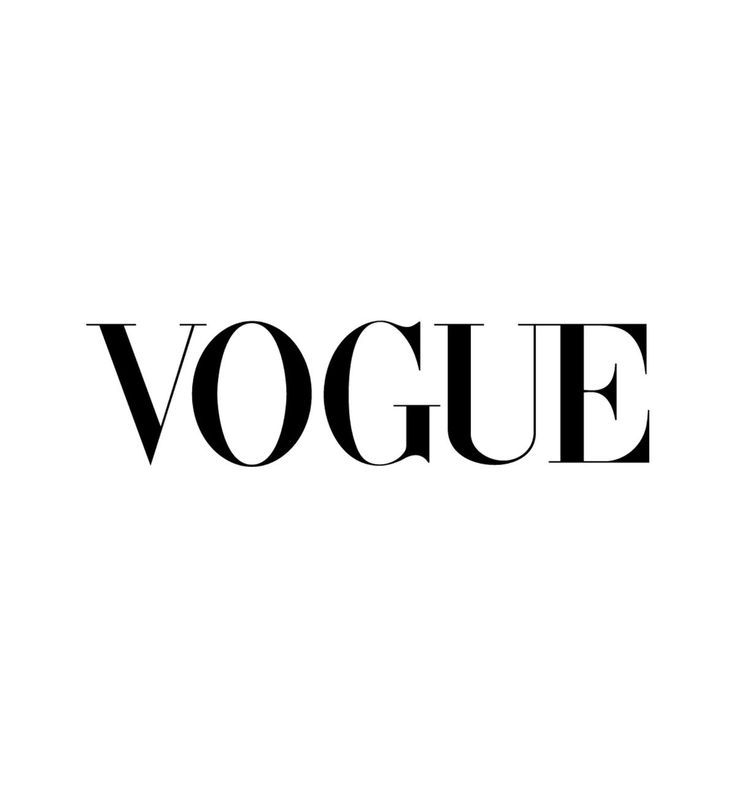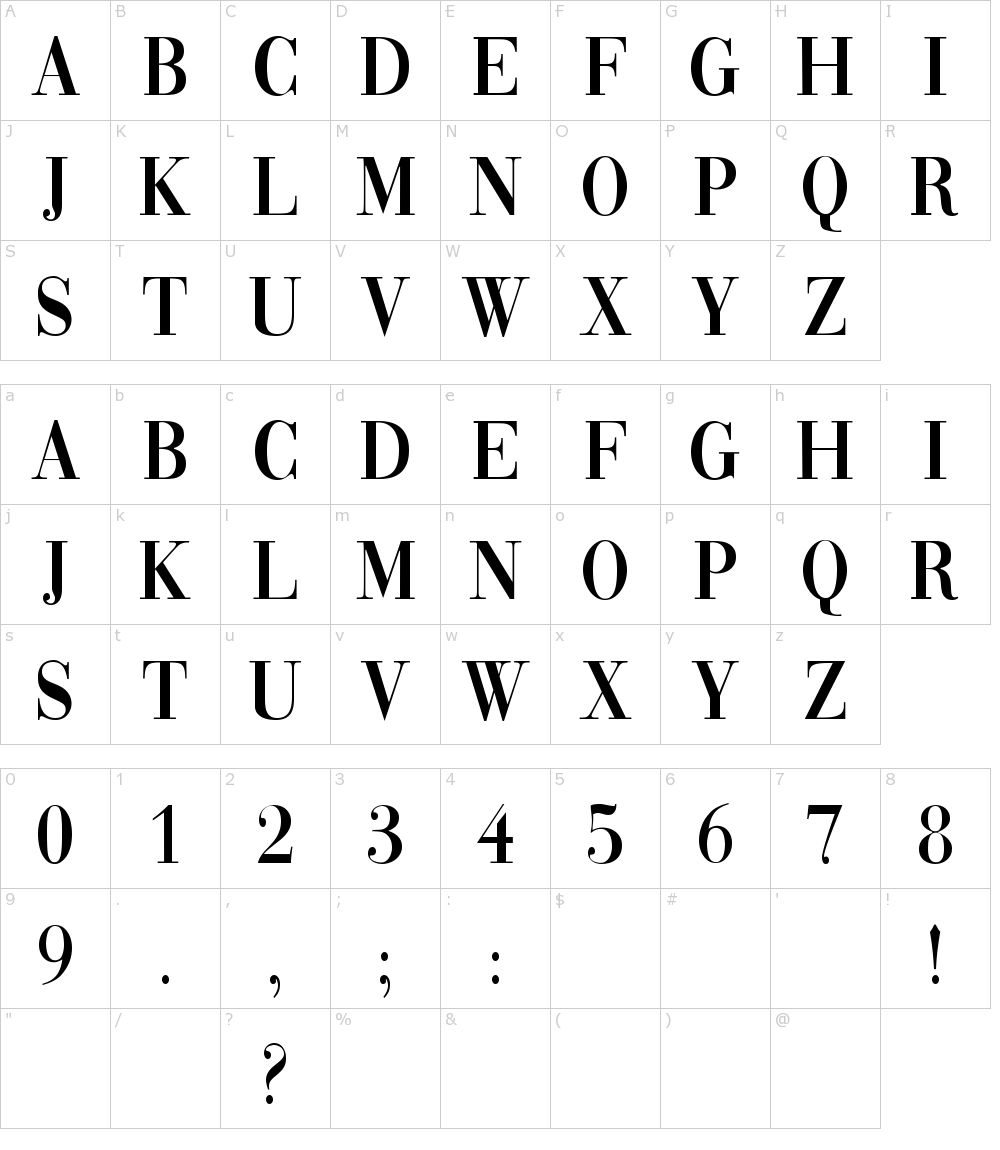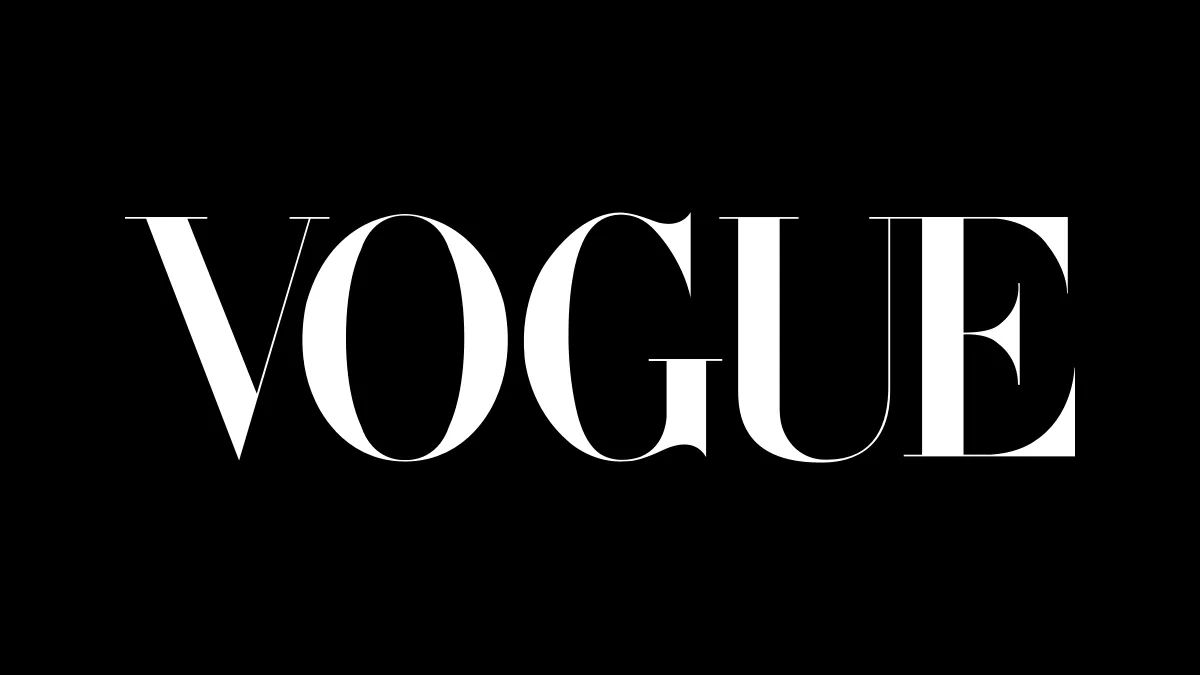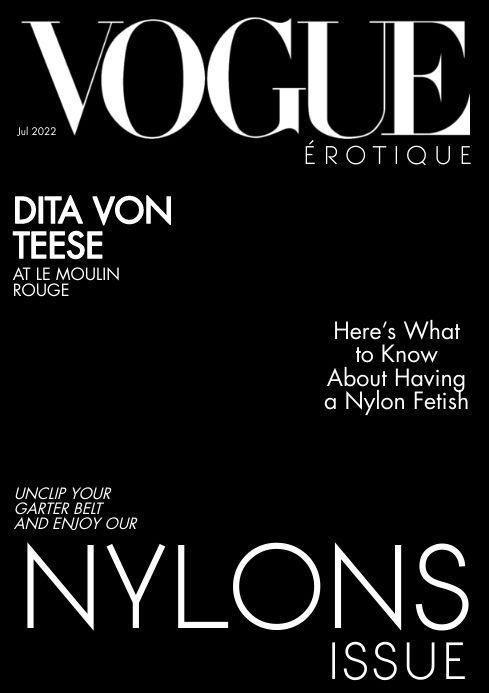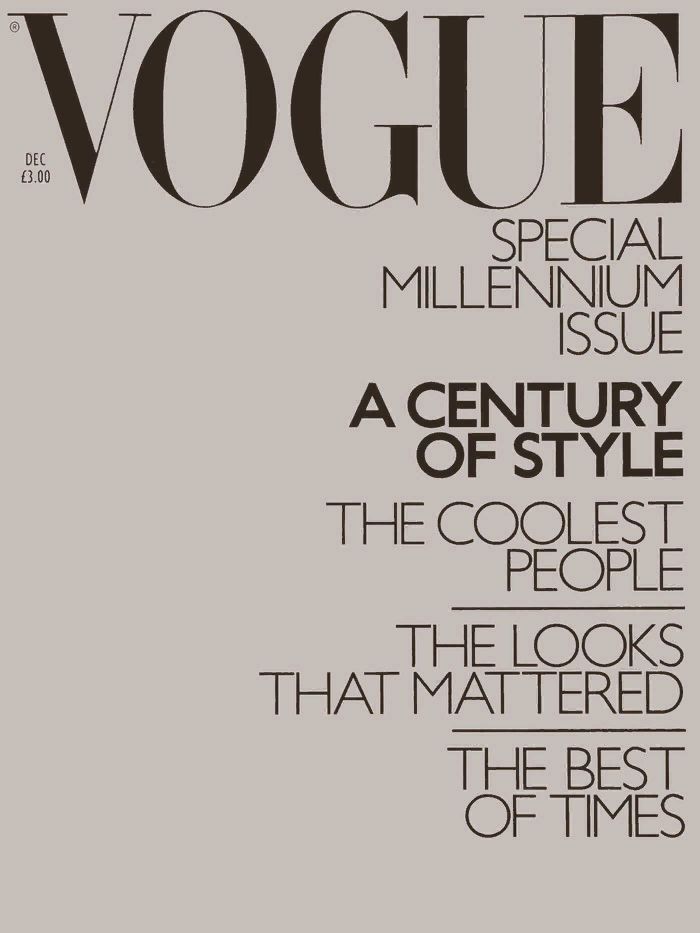
Kỹ thuật viên đồ họa khi thiết kế bao bì mỹ phẩm hay nhãn hàng xa xỉ thường gặp rắc rối do tệp tin Vogue font bị nhòe nét ở các đường thanh mảnh hoặc lỗi hiển thị trên chất liệu giấy mỹ thuật. Việc sử dụng nguồn dữ liệu kém chất lượng làm giảm đi vẻ quý phái và giá trị của bộ nhận diện thương hiệu. Xưởng In Viva cung cấp bộ Vogue font thời trang đa dạng định dạng, hỗ trợ quy trình gia công thành phẩm đạt độ sắc sảo cao trên nhiều bề mặt vật liệu.
Vogue font là gì và đặc trưng thẩm mỹ trong ngành in ấn?
Phông chữ Vogue là một hệ thống phông chữ thuộc dòng Modern Serif (chữ có chân hiện đại), lấy cảm hứng mạnh mẽ từ các thiết kế Didone như Didot hay Bodoni. Đặc điểm nhận diện của dòng phông này là sự tương phản cực lớn giữa nét thanh mảnh như sợi tơ và nét đậm vững chãi, mang lại cảm quan về sự thanh lịch, quyền quý và đẳng cấp quốc tế.
Hiện nay, các phiên bản Vogue free font được tinh chỉnh nhằm hỗ trợ tốt hơn cho việc hiển thị trên các bề mặt bao bì phức tạp. Cấu trúc chữ gọn gàng, các đường chân sắc sảo yêu cầu kỹ thuật in ấn có độ phân giải cao để không bị hiện tượng răng cưa.
Lưu ý chuyên môn: Khi sử dụng mẫu Vogue font cho mục đích in ấn hộp giấy cứng, kỹ thuật viên nên kiểm tra mật độ điểm ảnh ở kích thước thật. Việc duy trì sự rõ nét giữa các nét thanh và nét đậm là yếu tố quyết định tính thẩm mỹ cho ấn phẩm thương hiệu của đơn vị.
05 Công dụng nổi bật của phông chữ Vogue trong nhận diện thương hiệu
Sức hút của những đường nét sang trọng mang lại chiều sâu và giá trị riêng biệt cho các sản phẩm của doanh nghiệp trên nhiều phương diện truyền thông:
- Sản xuất bao bì mỹ phẩm và nước hoa cao cấp: Vogue font là lựa chọn phổ biến để thể hiện tên thương hiệu trên các dòng hộp giấy Ivory cán màng mờ. Sự tinh tế của phông chữ này giúp sản phẩm toát lên vẻ sạch sẽ, an toàn và chuyên nghiệp, khơi gợi niềm tin về chất lượng từ phía người tiêu dùng.
- Thiết kế và in ấn hồ sơ năng lực: Sử dụng phông chữ này cho các tiêu đề chương giúp tập tài liệu trở nên trang trọng hơn. Các đường nét chữ sắc sảo khi in Offset 5 màu hiển thị mịn màng, tạo thiện cảm lớn với các đối tác chiến lược khi tiếp cận thông tin doanh nghiệp.
- Sản xuất túi giấy thời trang và phụ kiện: Phông chữ này giúp các mẫu túi xách giấy trở nên thời thượng, bắt kịp xu hướng thiết kế tối giản toàn cầu. Lớp phủ bảo vệ sau in sẽ giữ cho các đường chân chữ Serif luôn rạng rỡ và hạn chế tình trạng bong tróc lớp mực.
- Khắc laser tinh xảo trên vật liệu kim loại: Những nét chữ dứt khoát của phông Vogue khi được khắc trên bề mặt vỏ bình giữ nhiệt hay USB tạo nên độ sâu tinh tế. Đây là giải pháp hiệu quả cho các dòng vật phẩm văn phòng mang phong cách sang trọng và thanh lịch cho các hội nghị cấp cao.
- In ấn thiệp mời và voucher VIP: Sự phối hợp giữa phông chữ Vogue rực rỡ và kỹ thuật ép kim nhũ vàng giúp thông điệp tri ân khách hàng trở nên nổi bật, khẳng định sự trân trọng của doanh nghiệp đối với người nhận ấn phẩm.
04 Sai lầm kỹ thuật thường gặp khi thực hiện in ấn phông chữ thời trang
Để thành phẩm sau in đạt độ mịn màng và trung thực với bản thiết kế, đội ngũ sản xuất cần chú trọng tránh những thiếu sót thường gặp sau đây trong quá trình chuẩn bị dữ liệu sản xuất:
- Sử dụng định dạng PNG nén cho in ấn khổ rộng: Nhiều thợ in sử dụng Vogue font PNG tải từ nguồn kém chất lượng để phóng lớn làm phông nền showroom. Hệ quả là các đường chân chữ thanh mảnh bị nhòe hạt, răng cưa, làm giảm đi giá trị cao cấp của thương hiệu. Cần ưu tiên dữ liệu vector để đảm bảo đường nét luôn sắc sảo ở mọi kích cỡ.
- Tối ưu đường Path cho gia công bế nổi: Một sai sót phổ biến là không làm mượt điểm neo trong file thiết kế khi yêu cầu dập nổi logo. Việc để dư thừa điểm neo khiến khuôn bế không sắc nét, dễ gây hiện tượng nhăn mép giấy hoặc rách sớ giấy mỹ thuật của bao bì, làm hỏng bố cục trang trọng của toàn bộ thành phẩm.
- Để mực bị loang ở các nét thanh khi in lụa: Đặc trưng của phông thời trang là nét cực mỏng. Nếu không kiểm tra độ lỏng của mực và độ phân giải lưới in, mực dễ bị tràn làm mất đi các khoảng trống tinh tế bên trong ký tự, khiến chữ bị bết màu và khó đọc trên chất liệu vải hay giấy nhám.